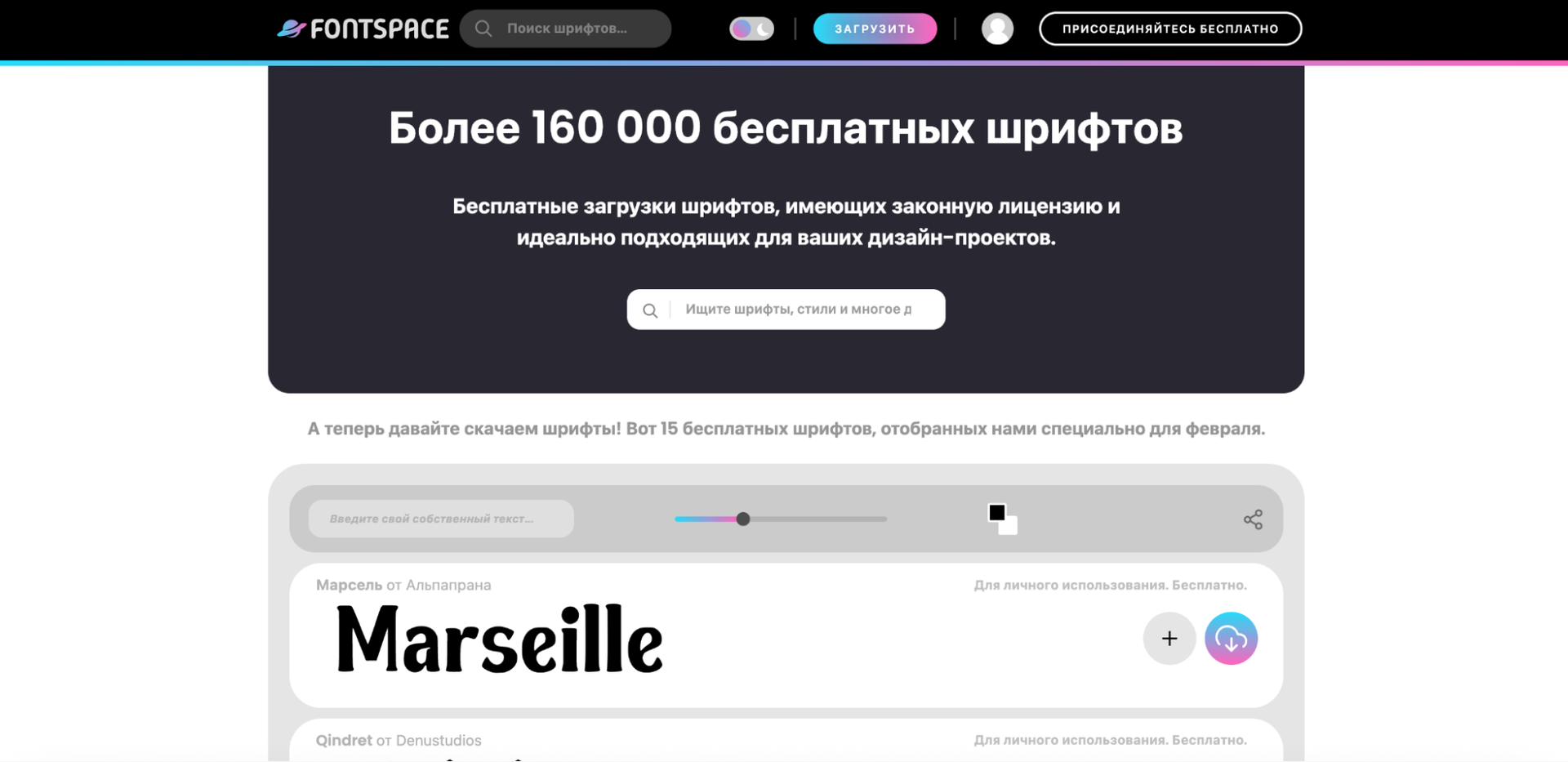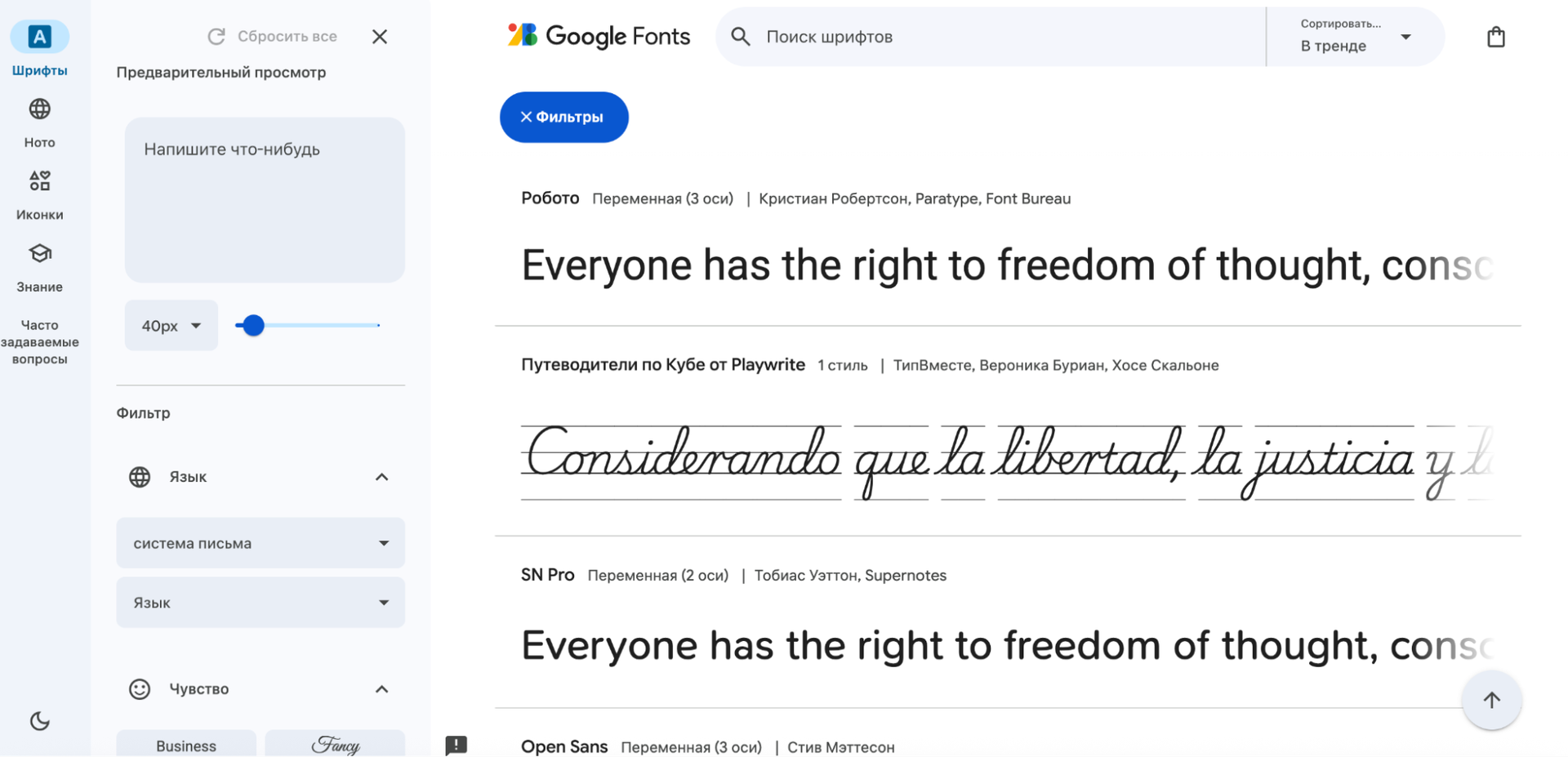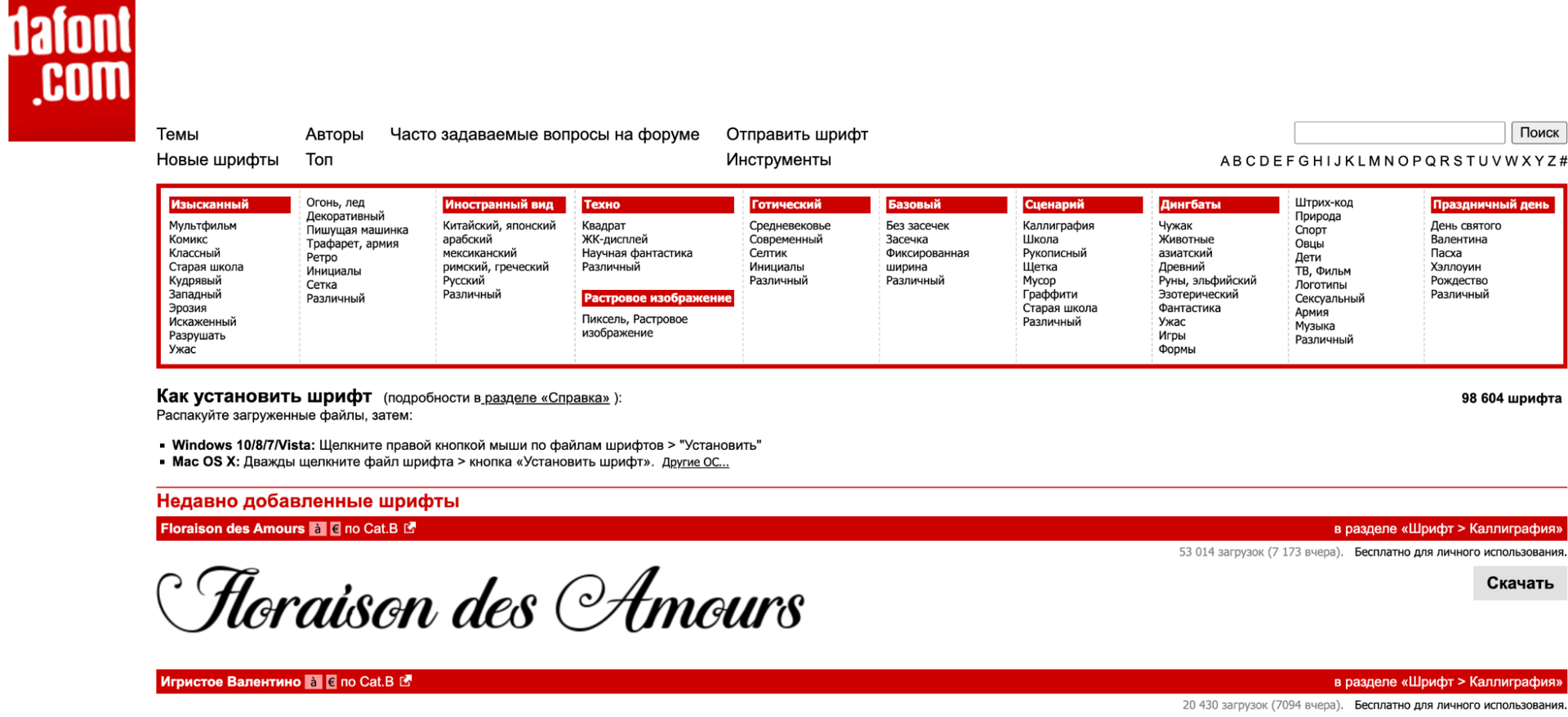
В момент, когда вы сталкиваетесь с необходимостью подбора шрифтов у вас встают две основные задачи.
1. Найти шрифт, который поддерживает кириллицу. Ведь с марта 2026 года, в России, в силу вступает закон, которые обязывает все бренды/продукты максимально русифицировать всё то, что попадает на глаза потребителю.
2. Найти шрифт, по разумной цене и с необходимым вам видом лицензии.
Ниже мы собрали подборку по ресурсам с бесплатными шрифтами. Для каждого ресурса указаны особенности и тип лицензии.
Проверенные сайты, где можно взять красивые шрифты бесплатно
Google Fonts: эталон для веб-проектов
Бесплатная, самая популярная и технически оптимизированная библиотека для цифровых продуктов. На январь 2026 года каталог насчитывает более 1500 шрифтов, практически все из которых распространяются под открытой лицензией SIL Open Font License (OFL). Эта лицензия разрешает свободное коммерческое использование, модификацию и распространение. Подробнее об условиях лицензии SIL OFL можно прочитать на официальном сайте фонда. Платформа предлагает продвинутую фильтрацию, включая отбор по поддержке кириллицы, что критически важно для русскоязычных проектов. Все шрифты оптимизированы для веба, поддерживают современные технологии вроде переменных начертаний (Variable Fonts) и подключаются одной строкой кода через CDN. Согласно исследованию HTTP Archive, свыше 85% всех веб-сайтов используют хотя бы один шрифт с Google Fonts, что делает эту платформу де-факто стандартом для веб-типографики.
FontSpace: гигантская коллекция с сообществом
Огромный архив, где тысячи дизайнеров делятся своими работами. Это отличный источник уникальных декоративных, рукописных и тематических шрифтов, которые редко встречаются в крупных библиотеках. Ключевая особенность необходимость всегда проверять лицензию на странице конкретного шрифта. FontSpace объединяет работы под разными типами соглашений: от свободных (SIL OFL) до строго ограниченных «только для личного использования». Система фильтрации, включая поиск по тегу «Cyrillic», упрощает выбор шрифтов для русскоязычных задач. Скачивание обычно доступно после бесплатной регистрации.
DaFont: классический архив с удобным поиском
Легендарный ресурс с мощной, хотя и несколько устаревшей, системой фильтрации по стилям (готические, граффити, ретро и другие). Идеален для быстрого поиска тематических и новых работ. Как и на FontSpace, тип лицензии (Free, Donationware, Shareware) указывается автором для каждого шрифта отдельно и требует обязательной проверки. Процесс скачивания простой, обычно в один клик без регистрации. Для ответственного использования рекомендуется скачивать шрифты только с официальных страниц авторов, где указаны точные условия.
CSTM Шрифты / ParaType: русскоязычная типографика
Российские студии, специализирующиеся на качественных кириллических шрифтах с полной поддержкой русского языка. Шрифты CSTM ориентированы на современный дизайн (например, семейство CSTM Fc Jules), ParaType — на классических гарнитурах типа PT Sans. Часть шрифтов бесплатна для некоммерческого использования, недорогая коммерческая лицензия и с техподдержкой. Лучший выбор для русскоязычных брендов и проектов с акцентом на локальную аудиторию.
Behance (Adobe): источник вдохновения и демо
Платформа-портфолио дизайнеров, где авторы выкладывают шрифты в виде творческих проектов или демо-версий. Здесь можно найти уникальные экспериментальные начертания, но лицензии часто ограничиваются личным использованием или требуют прямого контакта с автором. Используйте для поиска идей, тегов типа «бесплатный кириллический шрифт» и связи с создателями. Не является основным источником скачивания, но отлично подходит для нетривиальных находок.
1001 Шрифты: ежедневные обновления и подборки
Крупный агрегатор с 35 000+ шрифтами, удобными тематическими подборками («Хэллоуинские шрифты», «Свадебный сценарий») и ежедневными дополнениями. Лицензии разнообразны (многие из них бесплатны для личного использования, но есть и SIL OFL), всегда проверяйте шрифт на странице. Фильтры по стилям и кириллице работают отлично, скачивание без регистрации. Приспособление для определения настроения или тенденций, когда DaFont кажется однообразным.
Название платформы Особенности Тип лицензии Идеально для
Google Fonts >1500 шрифтов, оптимизация для веба, API, фильтр по кириллице Открытые лицензии (SIL OFL, Apache 2.0 и др.) Веб-сайты, цифровые продукты, коммерческие проекты
FontSpace Сообщество дизайнеров, много декоративных шрифтов Разная, требуется проверка (часто Free for personal use) Личные проекты, креативный дизайн
DaFont Огромный архив, популярен у дизайнеров, фильтрация по стилям Зависит от автора (Free, Shareware, Donationware) Неформальные проекты, хобби
Monotype (Fonts.com Free) Ограниченный доступ к премиальным коллекциям Бесплатно с ограничениями по трафику / демо-доступ Тестирование шрифтов, небольшие сайты